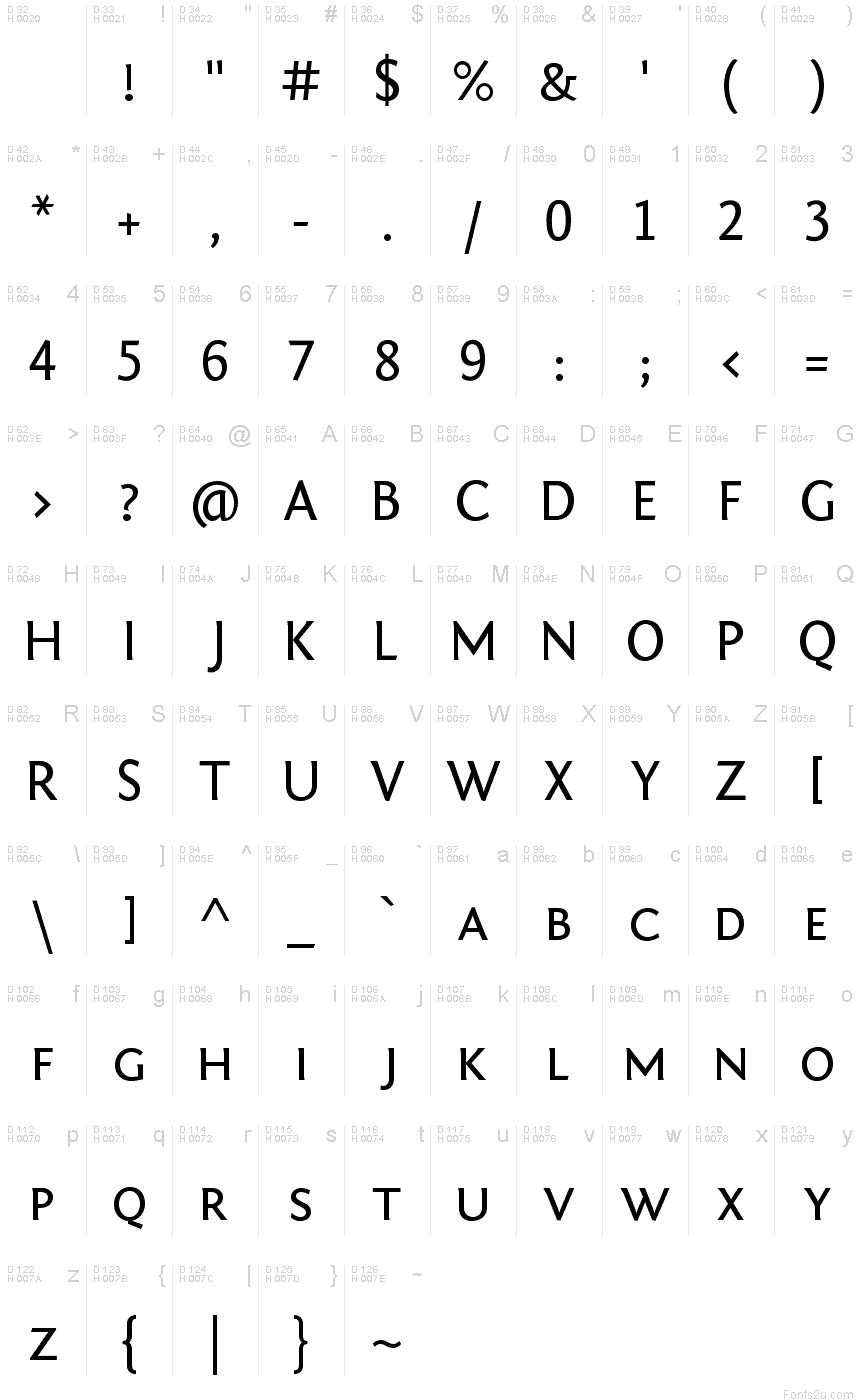
Fontin Sans CR SC, de Jos Buivenga, é uma fonte sans-serif humanista gratuita com maiúsculas nítidas, formas circulares amplas e proporções levemente variadas que suavizam a sua construção, de outro modo disciplinada. O traçado aparenta ser calmo, aberto e cuidadosamente desenhado.
Capas editoriais são uma escolha particularmente adequada, uma vez que as formas bem medidas combinam com harmonia ao lado de fotografias e servem a revistas culturais, relatórios anuais e programas de exposições. Essa mesma sobriedade pode apoiar a identidade de marca de estúdios de arquitetura ou produtos orientados pelo design, conferindo a logotipos e embalagens uma identidade serena que parece menos mecânica do que uma sans-serif estritamente geométrica.